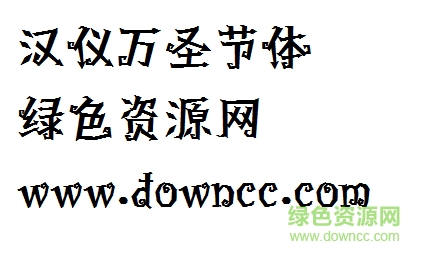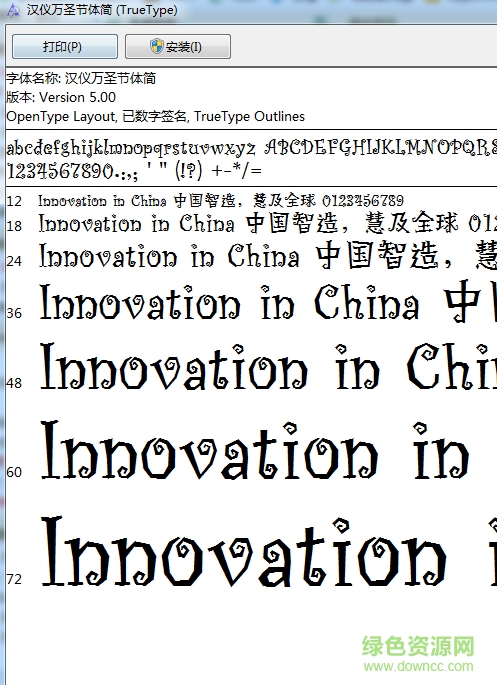
漢儀萬圣節(jié)體簡(jiǎn)字體
漢儀萬圣節(jié)體是一款漢儀系列萬圣節(jié)特有字體軟件,源自萬圣節(jié)趣味驚悚搞怪靈感,整體給人非常酷炫的感覺,十分耐看,喜歡就到綠色資源網(wǎng)下載體驗(yàn)吧!
漢儀萬圣節(jié)體字體介紹預(yù)覽
字體風(fēng)格: 休閑、有趣、可愛、快樂、驚悚;
推薦場(chǎng)景: 標(biāo)志、廣告、游戲動(dòng)漫、萬圣節(jié)、情人節(jié)。
漢儀萬圣節(jié)體
官方介紹
漢儀萬圣節(jié)體是一款應(yīng)用于藝術(shù)設(shè)計(jì)方面的簡(jiǎn)體中文字體,該字體筆畫粗壯,尾部的甩尾有力且有豐富的筆觸細(xì)節(jié),大字效果突出且引人注目;并且最大程度還原作者書寫字形,細(xì)節(jié)表現(xiàn)完整,且字庫(kù)完整,可以廣泛應(yīng)用于名片設(shè)計(jì)、新聞媒體、宣傳海報(bào)、ppt、影視制作以及內(nèi)容用字等領(lǐng)域。
小編點(diǎn)評(píng)
漢儀萬圣節(jié)體專為萬圣節(jié)搞怪嚇而生,通過此字體可以制作相應(yīng)的恐怖圖片配字,驚悚氣息十足,歡迎廣大網(wǎng)友下載體驗(yàn)!